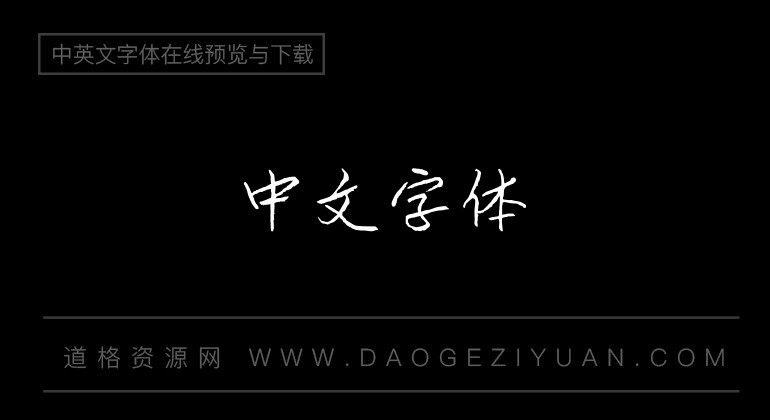
游狼美钢行书是一款传统行书字体,它的特点是基于经典的行书字体,结合现代技术,重新设计而成的一款字体。它的字形细腻,线条优美,笔画流畅,曲线圆润,笔划清晰,表现力强,可以满足不同的设计需求。文件名:YouLangMeiGangXingShu-Jian-1.ttf
游狼美钢行书是一款非常不错的手写艺术字体,具有很好的视觉感,适合于文化类的宣传设计、商业类品牌的广告和产品包装设计以及个性化文字排版等较多场景。